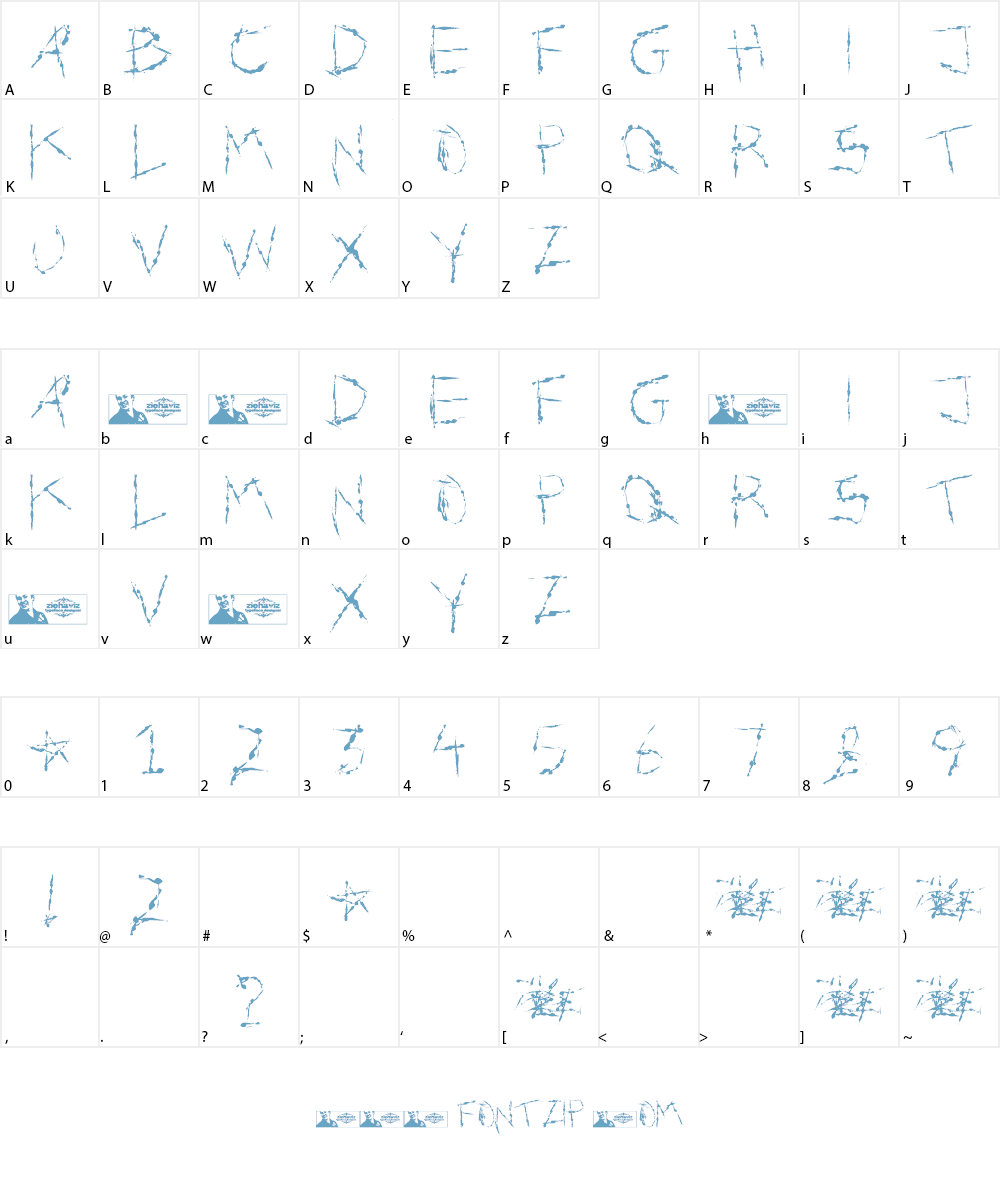
Terinspirasi dari semangat membara para pejuang dan pahlawan Bangsa Indonesia dan Hari Kemerdekaan Bangsa Indonesia 17 Agustus 1945! MERDEKA atau MATI!